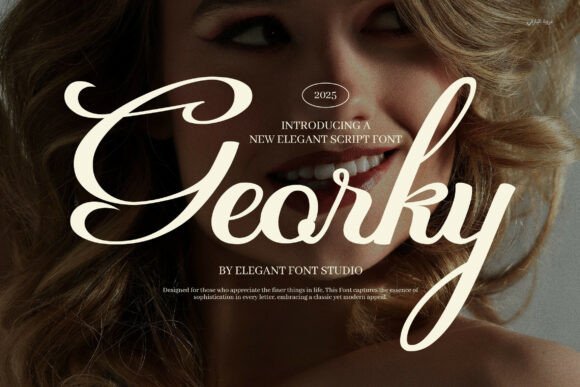
Georky Wedding Script
Створений з високою точністю, Georky Wedding Script забезпечує чисті вектори, плавну типографіку та комерційну ліцензію для вашого спокою.